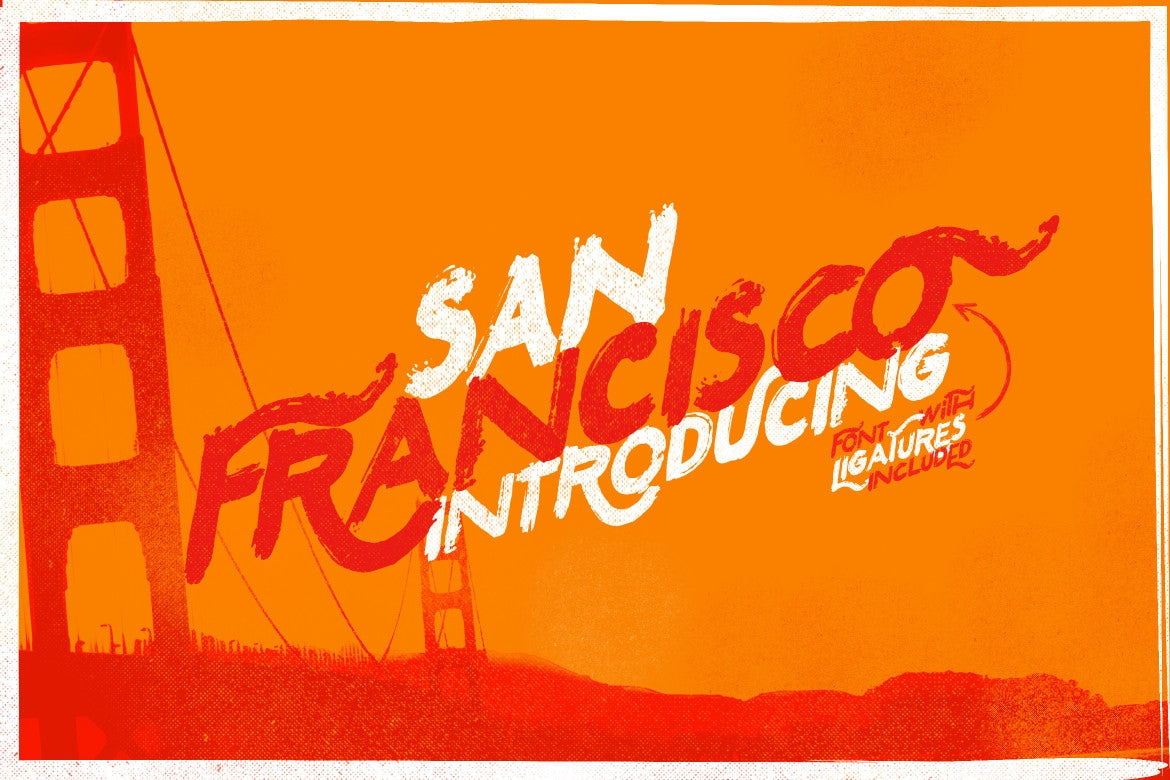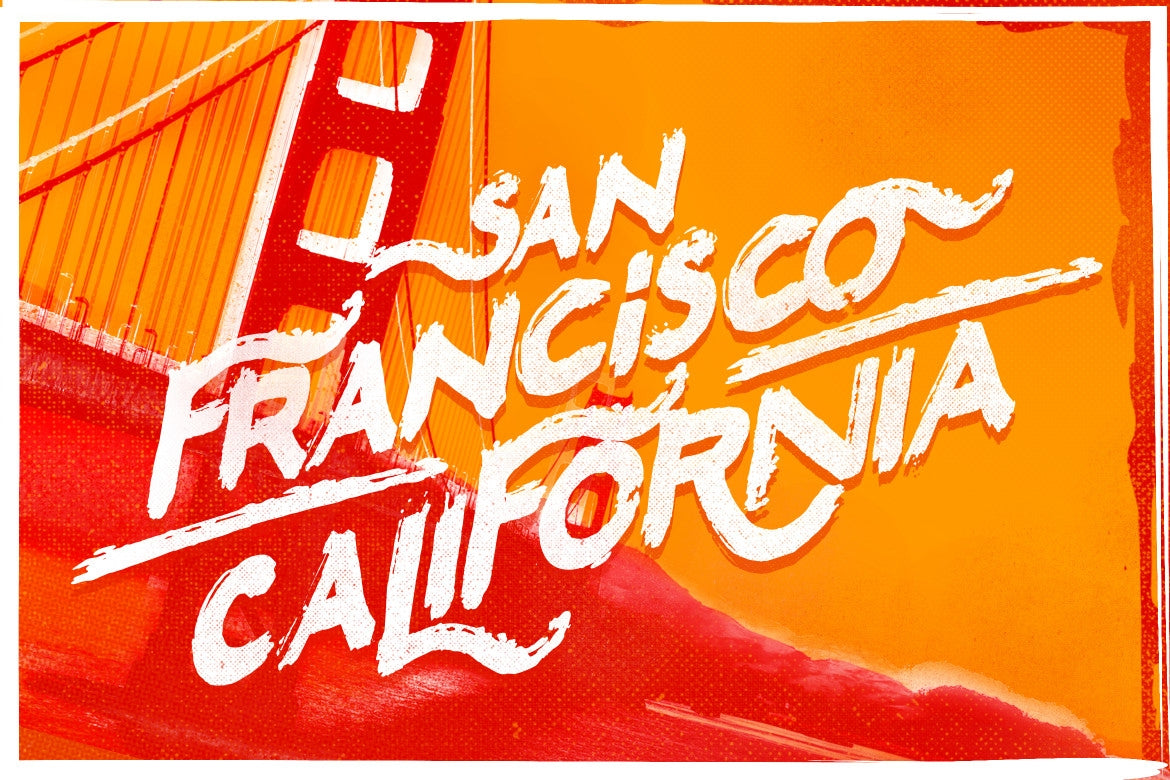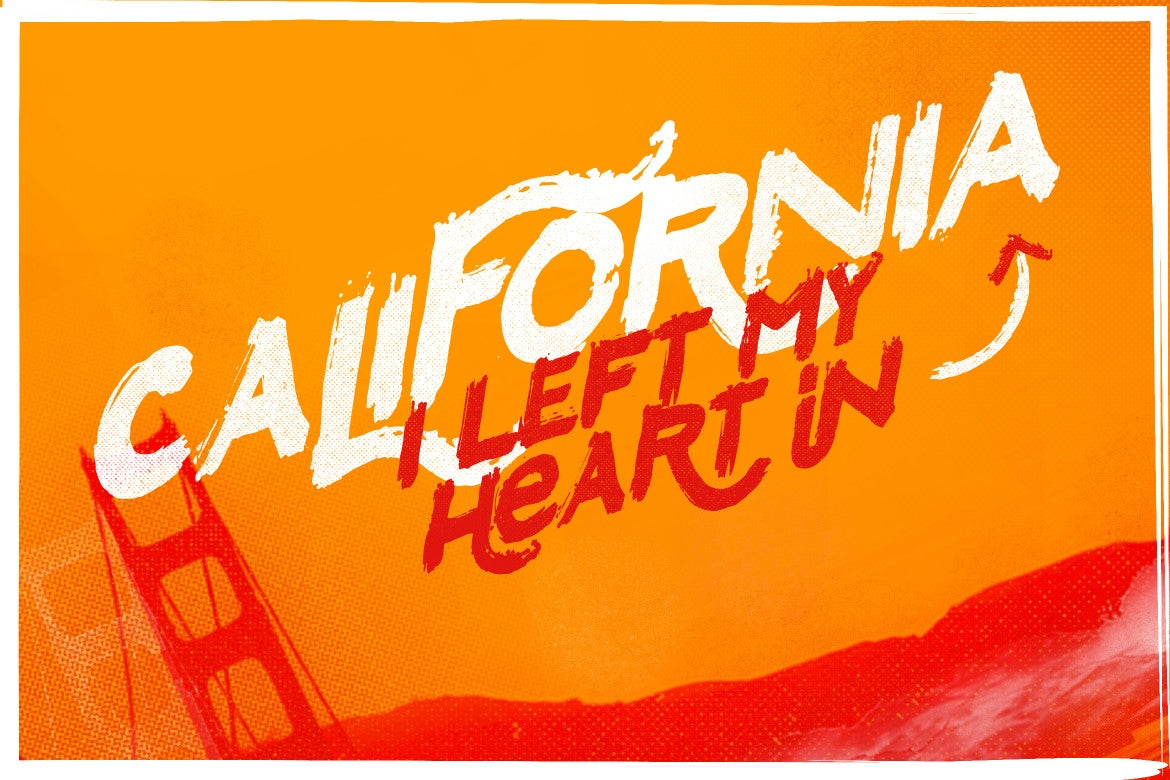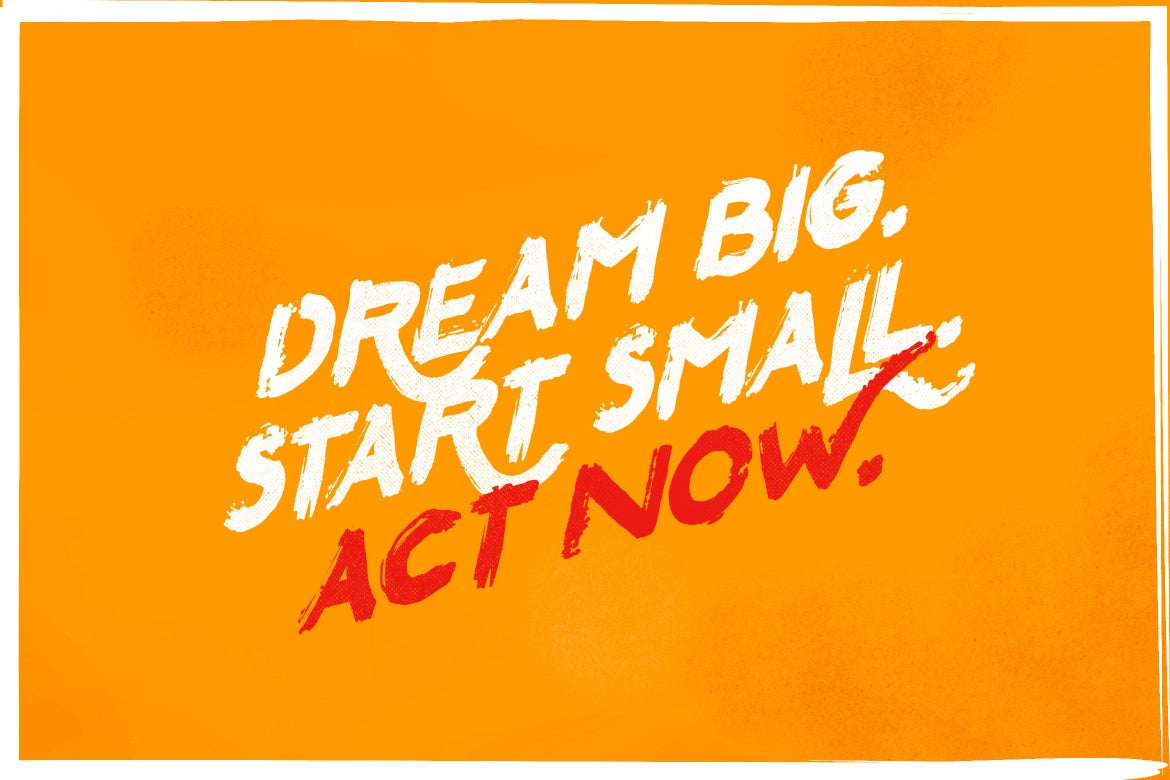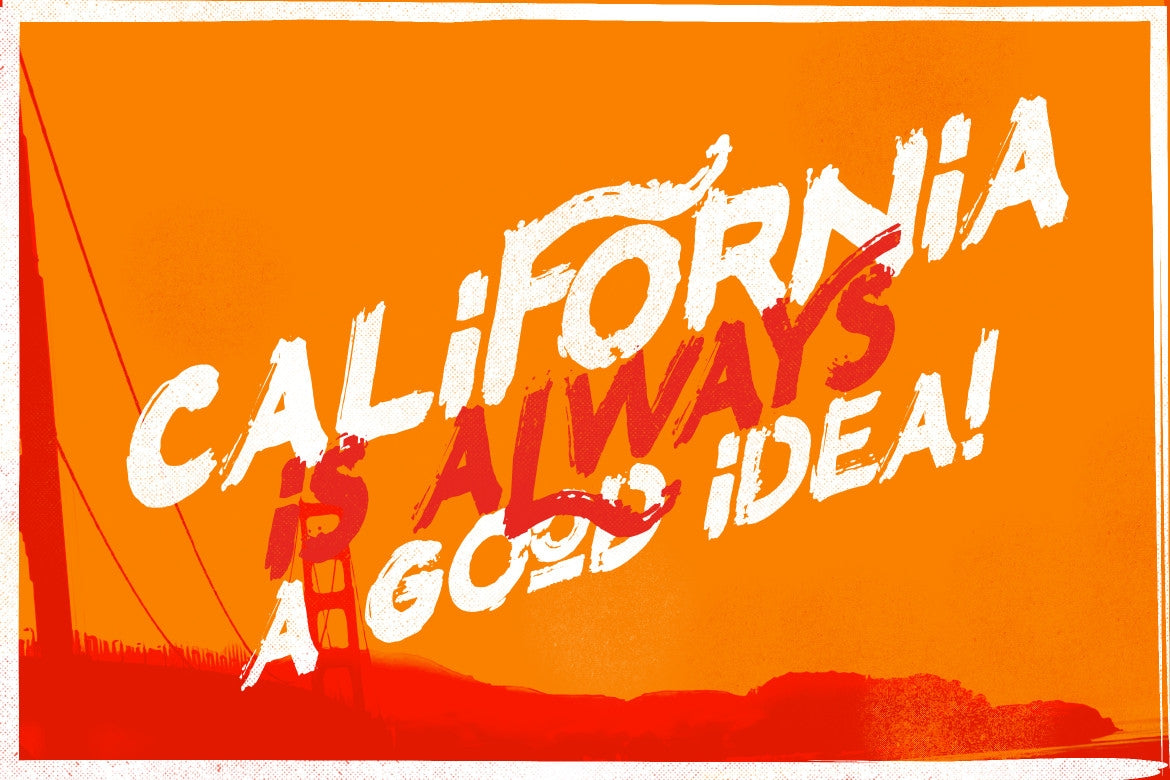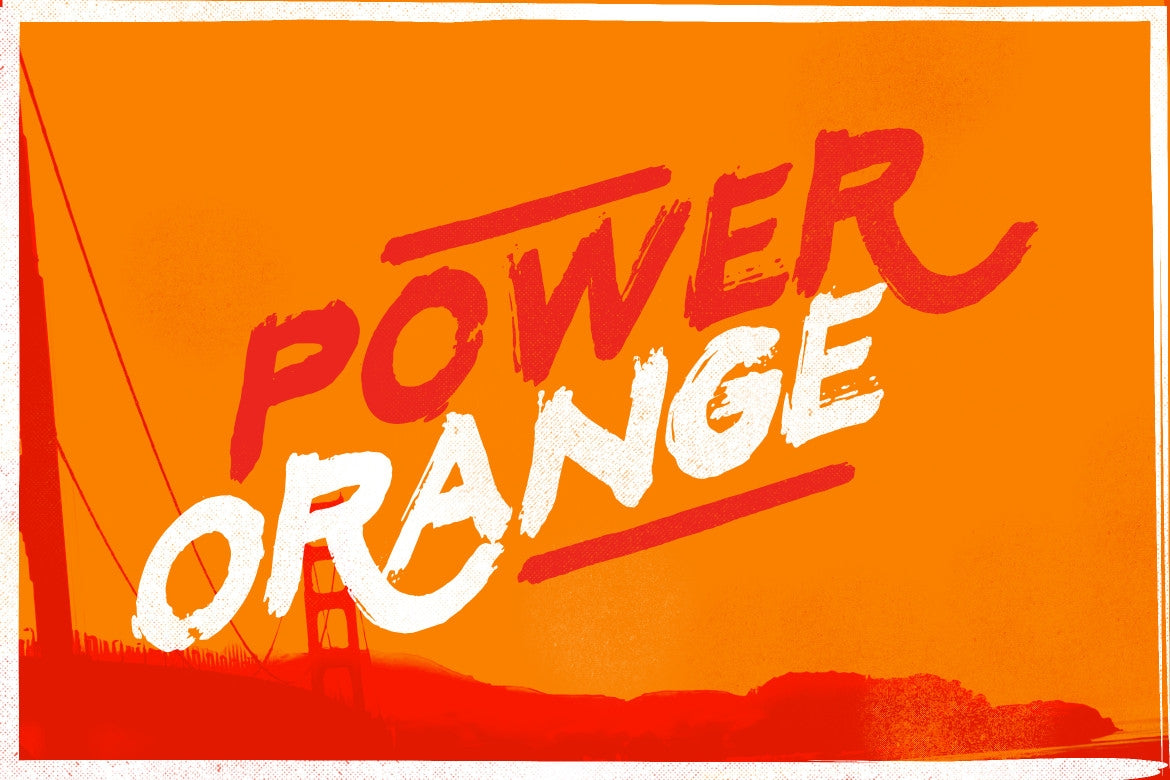
Fuente de San Francisco
San Francisco Font es una nueva fuente de Leo Supply Co., una fuente con un conjunto de caracteres simples, grunge, retro, vintage, experimentales y versátiles.
Viene con 3 estilos, uno regular, alto y cursiva para crear una opción para los diseños.
Para crear la hermosa combinación, mezcle las letras mayúsculas y minúsculas y luego mézclelas con los glifos alternativos y de ligadura.
La fuente San Francisco incluye un conjunto completo de mayúsculas y minúsculas, además de compatibilidad multilingüe, símbolos monetarios, numerales, puntuación y ligaduras. Combina las mayúsculas y minúsculas e incorpora garabatos estilo Memphis para lograr el aspecto que buscas. Después, combínala con los glifos alternativos.
• Conjunto de caracteres de la A a la Z
• Números y puntuación (estándar OpenType)
• Acentos (caracteres multilingües)
• Alternativas estilísticas y ligaduras
Ideal para mensajes llamativos. Hecho con marcador plano, añadiendo movimientos realistas. Ideal para logotipos, etiquetas de nombre, citas manuscritas, empaques de productos, artículos promocionales, redes sociales y tarjetas de felicitación. También es ideal para diseñar camisetas y otras prendas de vestir.